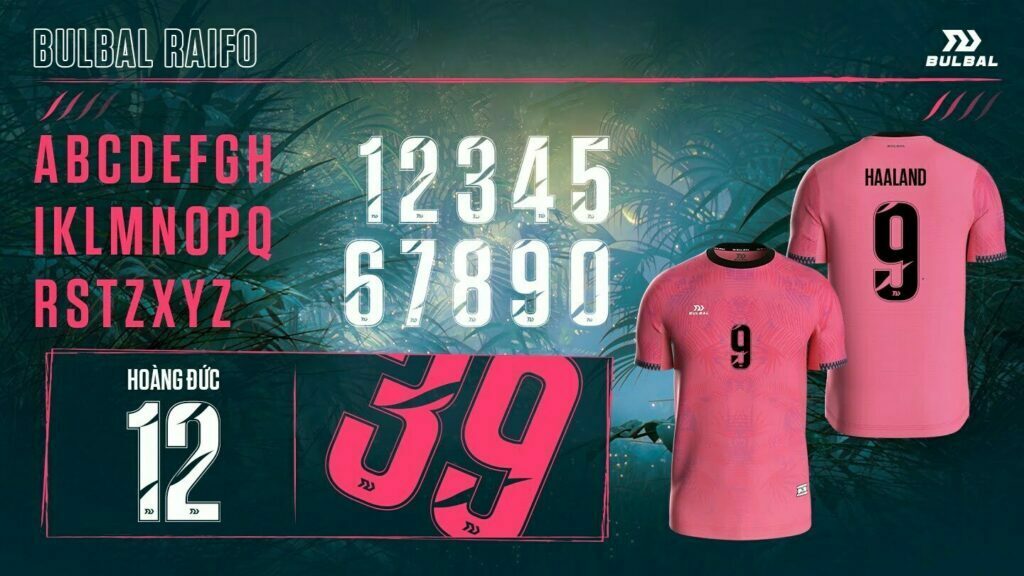
Một bộ áo đá bóng đẹp không chỉ có màu sắc, hoa văn và logo, mà nó còn có sự kết hợp độc đáo của những font số. Vậy những font số nào đang được giới trẻ yêu thích nhất trong những năm gần đây? Sau đây mời các bạn cùng mình điểm qua những font số áo đá bóng ĐỘC ĐÁO nhất Việt Nam nhé!
Bộ Font Số Bulbal Xona
Được thiết kế độc quyền bởi nhà sáng tạo Bulbal, bộ font số này lấy cảm hứng từ sóng âm – một làn sóng mang đến nguồn năng lượng mạnh mẽ thể hiện sức công phá vượt trội đỉnh đạt của các cầu thủ.
Bộ font Bulbal Xona được thiết kế theo ký tự Tiếng Việt chính vì vậy mà các anh em dễ dàng in ấn họ và tên các thành viên một cách thuần Việt, giúp mọi người dễ đọc hơn.
Bộ Font Số Bulbal Raifo
Lấy ý tưởng từ “Hệ sinh thái nhiệt đới” nhà thiết kế Bulbal đã cho ra mắt một bộ font số, thể hiện sức sống vượt trội mang tên BULBAL RAIFO và cũng chính BST này đã làm cho hàng loạt anh em cầu thủ mê mẩn săn lùng đặt in liên tục.
Bộ Font Số Bulbal 6 City
Với mong muốn nâng cao tinh thần thể thao cho các bạn trẻ thành phố, BST ÁO BÓNG ĐÁ BULBAL 6 CITY ra đời với những góc cạnh sắc nhọn thể hiện cá tính mạnh mẽ và nhiệt huyết của tuổi trẻ.